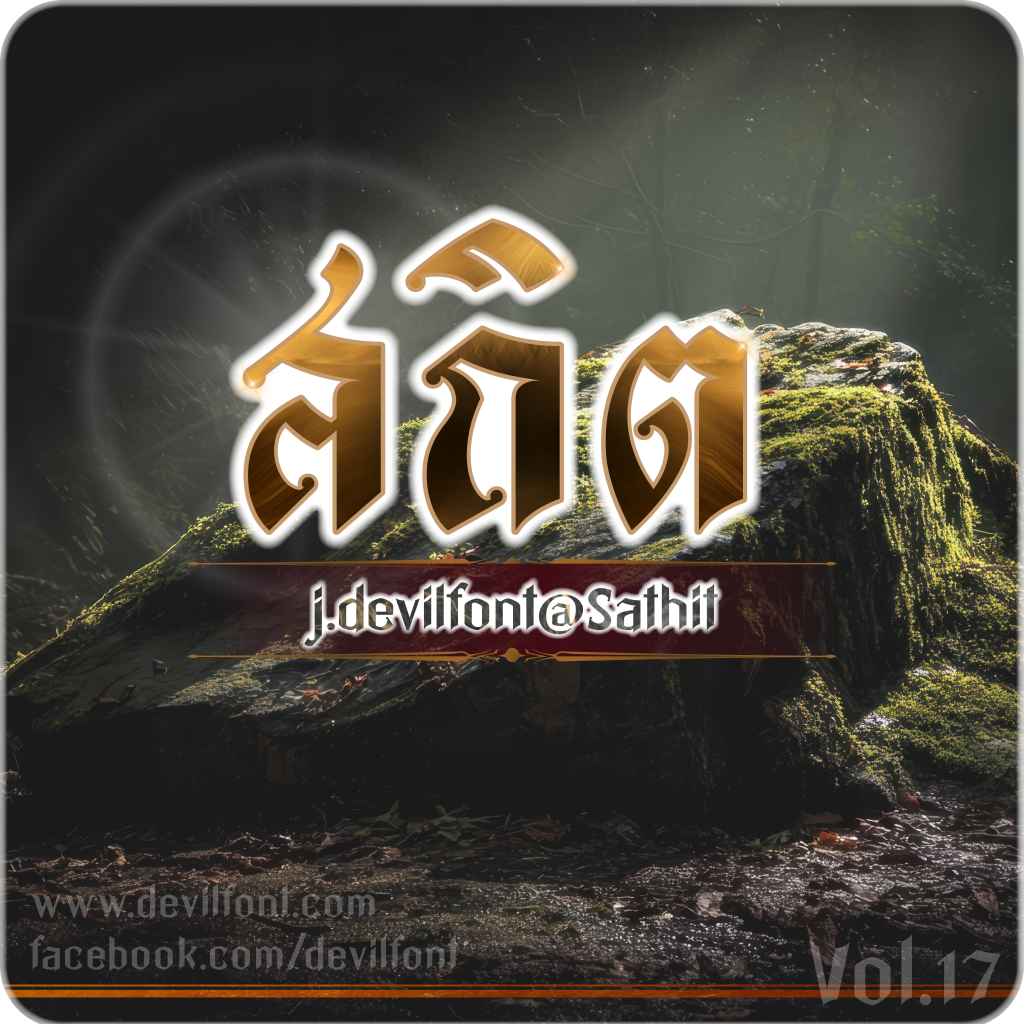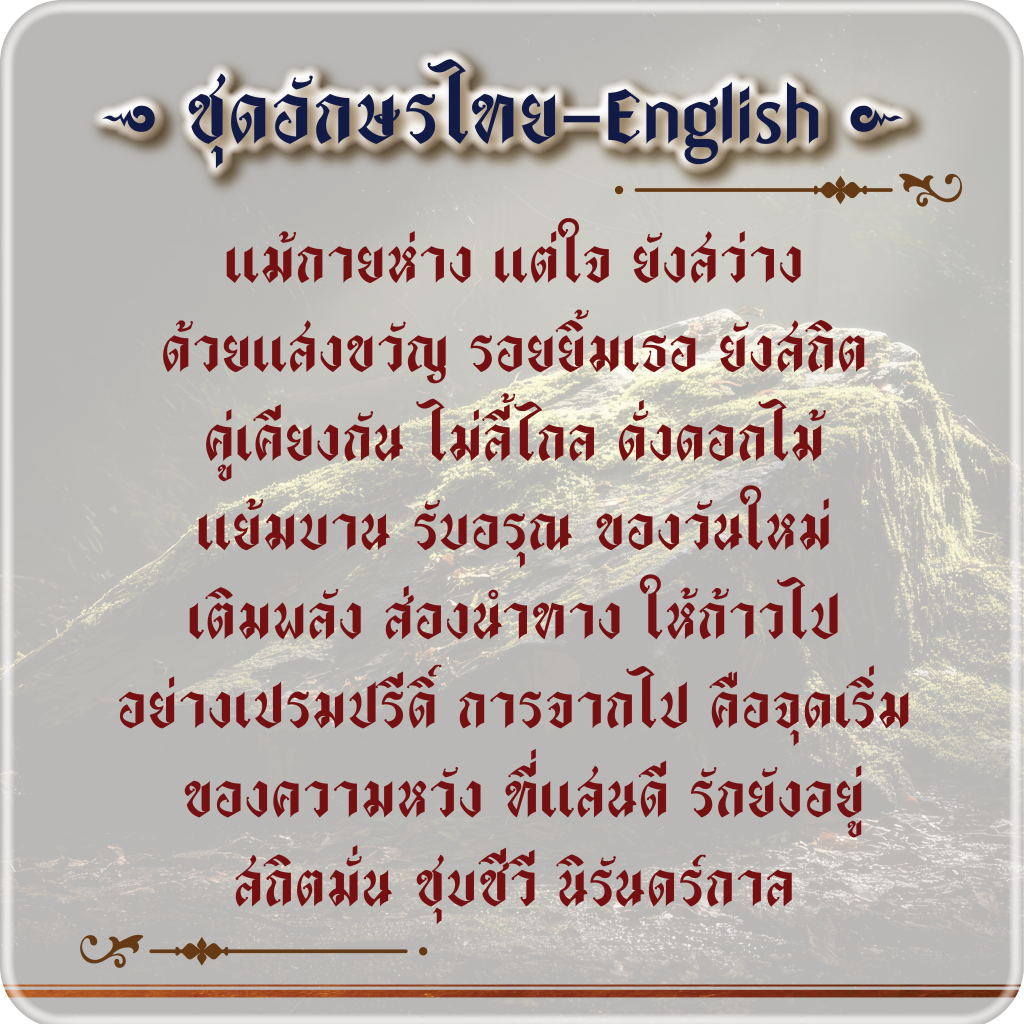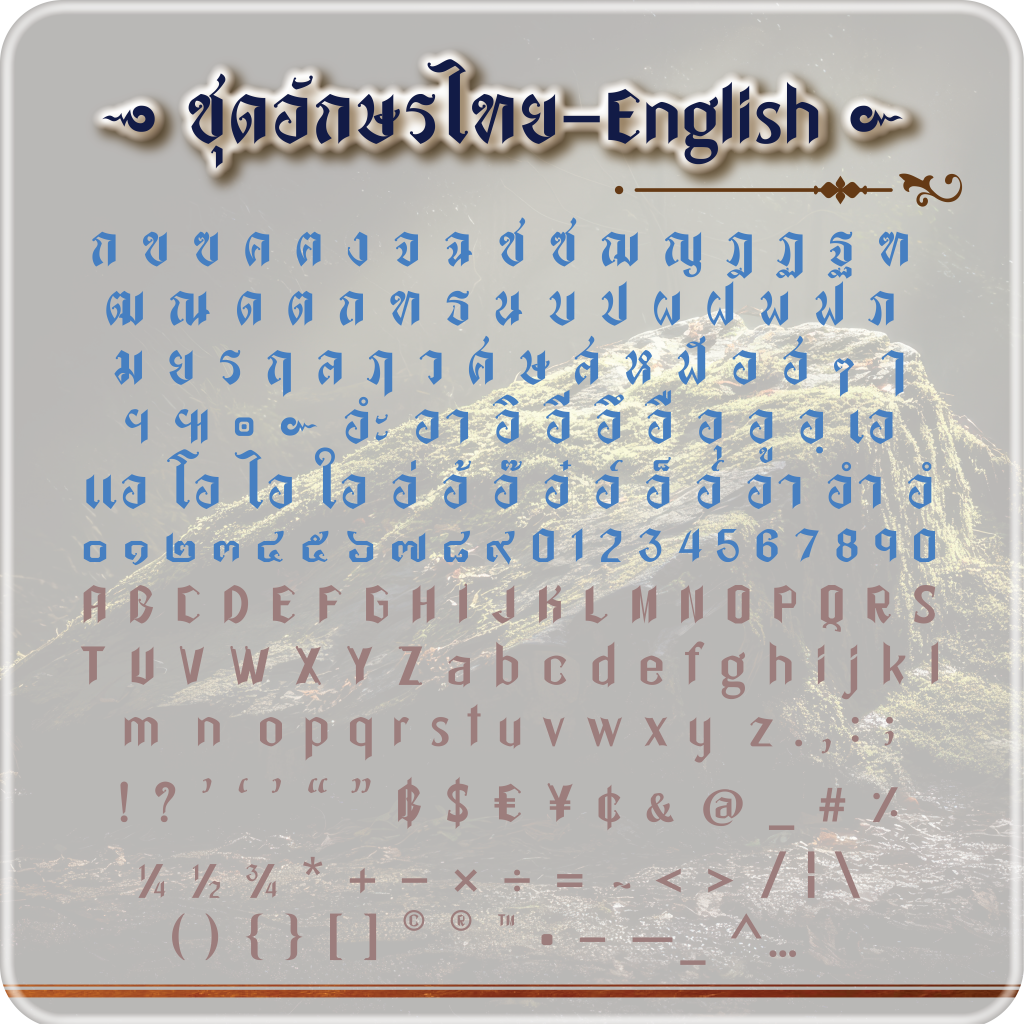
j.devilfont
ฟอนต์ สถิต
ฟอนต์ สถิต ผลงานฟอนต์ชุดที่ 17 – ลักษณะฟอนต์ไทย พาดหัว งานป้าย งานไม้ งาน cnc บทกลอน ป้ายร้านค้า สายมู ปกนวนิยาย นิตยสาร เทศกาล ศาลเจ้า ของโบราณ โลโก้ สกรีนเสื้อ แสดงงานพิธี สารคดี สื่อโฆษณา แบรนด์สินค้า ความเป็นเอกลักษณ์ไทยโบราณร่วมสมัย
รายละเอียด ฟอนต์สถิต
ใช้งานด้วย kerning ปรับระยะห่างของชุดอักษรทั้งไทย-อังกฤษ
ใช้ mark ในการจัด อักษร+สระ+วรรณยุกต์ เพิ่มการไล่ระดับสระ+วรรณยุกต์ อัตโนมัติ
เพิ่มลูกเล่นที่ โ ใ ไ ที่ยืด-หด และเปลี่ยนรูปในเวลาพิมพ์อัตโนมัติ
ตัวอักษรมีหาปรับหางสั้นเองเมื่อพิมพ์  สระอิ อี อึ อื  ่  ้  ๊  ๋  ์  ็  ั  ํ
ตัวอักษรมีหางปรับหางสั้นเองเมื่อพิมพ์  ตัวที่คำตัวอักษรที่มีหางเช่น สี่ปี หาง ส จะไม่ทับกับสระอีบน ป  / ป่ป้ป๊ป๋ เปลี่ยนรูปทรง
เพิ่มวิธีการพิมพ์ โคมูตร ( ๛ ) กด  ฯ147963 ต้องการโคมูตรตัวพิเศษกลับด้าน 147963ฯ
เพิ่มวิธีการพิมพ์ตัวบาลี ญ ฐ แบบไม่มีเชิง ด้วยการกด ญฯฯ  /  ฐฯฯ  จะได้ตัวที่ไม่มีเชิง
ตัวอักษรอังกฤษ ก็มีการปรับค่าแก้โค้ดให้ไม่มีหางทับกัน แบบ auto